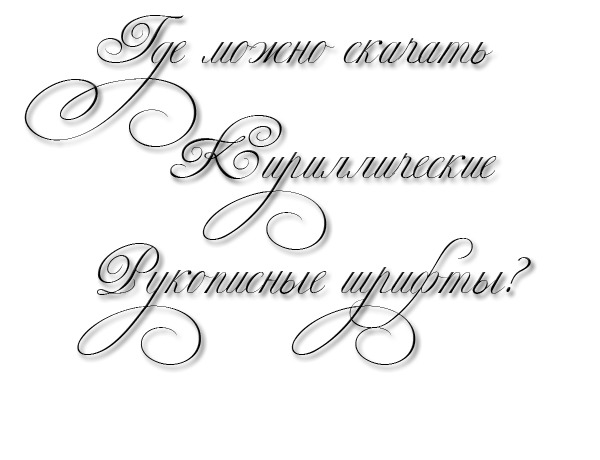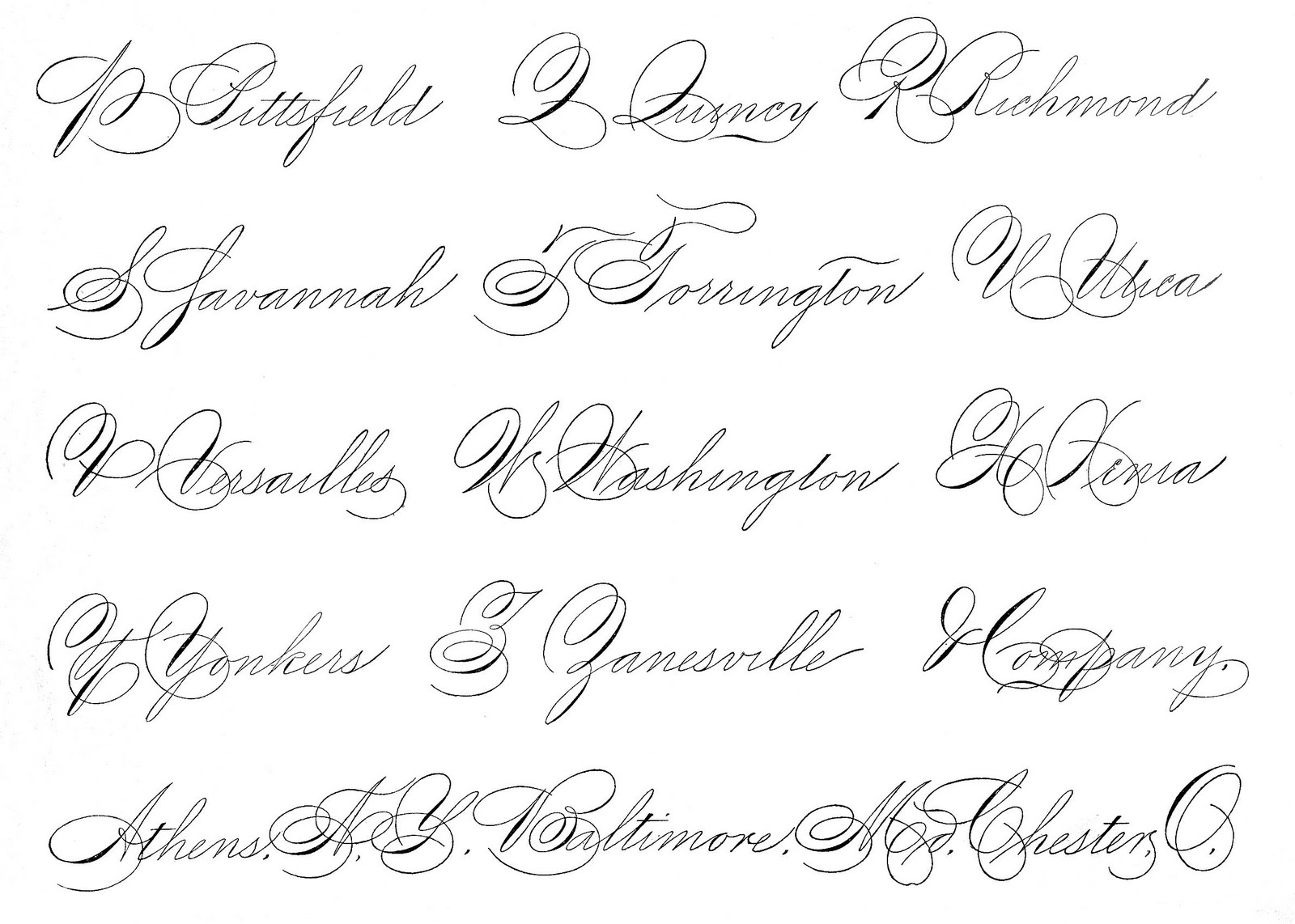
Скрипты имитируют написанные от руки буквы, цифры и другие символы. Именно этим объясняется их название. Шрифты востребованы в веб-дизайне и вёрстке макетов для печати. Вид шрифтовых наборов определяется по имитируемому инструменту для письма.
Дополнительно рукописные шрифты делятся на связные и несвязные. В первом случае буквы соединяются между собой, а во втором символы стоят в строках отдельно. Существуют и полусвязные шрифты. Объединение выполняется по конкретным частям или сторонам знаков. Что касается области применения, то к шрифтовым комплектам часто прибегают для привлечения внимания или оформления учебников.
К минусам шрифтов относят затруднённое визуальное восприятие, что снижает удобство чтения набранных текстов. Зато скрипты превосходно подходят для придания значимости заголовкам, цитатам, отдельным строкам или маленьким отрывкам классических литературных произведений. С их помощью часто оформляют ресторанные меню, логотипы фирм, коммерческие презентации, названия глав и т. п.
По начертанию шрифты делятся на несколько больших групп. Формальные скрипты основываются на литерах из книг писателей 17-18 веков.
Написание стилизуется под выведенные пером буквы. Толщина линий – равномерная. Наборами пользуются, когда необходимо сымитировать рукопись и пропись или оформить грамоты и приглашения на торжественные события вроде свадеб и юбилеев.
Вторая группа – казуальные шрифты, которые воспроизводит мокрую кисть, отличаются свободным начертанием и иногда имеют линии с переменной толщиной. Первые наборы появились в начале прошлого столетия. Популярность комплектов возросла после широкого распространения фотографических композиций в 50-х годах. Сегодня скрипты нередко используются для рекламы и стилизации под гравировку.
Шрифт похожий на рукописный русский в ворд
Хочу рассказать вам и показать на конкретном примере как сделать рукописный текст на компьютере при помощи текстового редактора Microsoft Word.
Также вы узнаете, как распечатать данный текст на принтере в формате тетрадного листа в клеточку.
Прежде чем приступить к практическим действиям нужно скачать рукописные шрифты для Word, которые работают как с кириллицей, так и с латиницей, чего не скажешь о стандартных.
Установка шрифтов
1. Способ для современных ОС.
После того как вы скачали Zip архив «fonts.zip» распакуйте его в специально заранее созданную для этого папку.
Обратите свое внимание, что в архиве помимо шрифтов, имеющих расширение «ttf» есть файлы с расширением «png» это картинки на которых показан как выглядит каждый шрифт. Для просмотра просто произведите двойной клик ЛКМ по файлу.
Теперь выберем понравившейся шрифт, я рекомендую выбрать все. Зажимаем клавишу Ctrl проставляем галочки ЛКМ на файлах с расширением «ttf».
Вызываем ПКМ контекстное меню, нажимаем пункт Установить (если вы работаете с учетной записью обычного пользователя, то потребованною введите пароль администратора).
Вот и все после перезагрузки компьютера можно приступать к написанию, но сначала рассмотрим алгоритм второго способа, предназначенного специально для «ретроградов», не использующих современные ОС.
• Выделяем шрифты вышеописанным способом, копируем их;
• идем по пути: C:WindowsFonts;
• при помощи горячих Ctrl+V вставляем в папку Fonts.
Не забываем перезагрузить ПК.
Создадим тетрадный лист в клетку
ReskaGraf Шрифт Разработанный Оливье Зитуном, популярным благодаря своей другой работе под названием Zit Graffiti, шрифт имеет привлекательное сочетание заглавных и строчных букв, а также цифр.
Эти блочные шрифты, созданные известным дизайнером Оливье «Зитун» D, являются смелыми и эффектными. Набор состоит только из прописных букв.
JustFistЭто богатое предложение, состоящее из двух комплектов.Первый имеет традиционный вид, а второй набор создает ощущение капающей краски с каждой буквы. Смелый и красивый, подчеркните, используя этот шрифт.